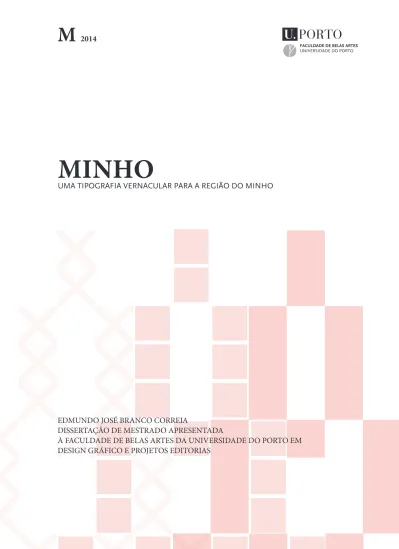
MINHO
UMA TIPOGRAFIA VERNACULAR PARA A REGIÃO DO MINHO
EDMUNDO JOSÉ BRANCO CORREIA
The main purpose of this dissertation is to show how the design of a typeface can reflect the identity of a region; in this case the region of Minho.The present work shall be guided by the question of whether a typeface can reflect the cultural identity of a place.
Minho region has strong traditions such as the gastronomy, the architectural heritage, religious festivities and folk dance. The folk dance is strongly related to “lenços dos namorados” ( Lovers’ han-dkerchiefs), where one can see some inscriptions related to the the-me of Love written in a poetic way.
The studied began with an analysis of the lettering used in the handkerchiefs and a vernacular base was used to draw the typeface. Thus, there was a relation between the typeface created by the lette-ring and the cultural identity of the place.
O propósito principal desta dissertação foi o desenho de uma tipogra-fia, que transparecesse a identidade da região do Minho. Teve como questão orientadora, como a tipografia pode refletir a identidade cul-tural de um local.
O Minho é uma região de fortes tradições: desde a gastronomia, passando pelo património arquitetónico, comemorações religiosas e, sobretudo o folclore. Foi através do folclore que chegamos aos lenços de namorados, e às suas inscrições em forma de verso, sempre relacio-nadas com o amor e a conquista.
Foi a partir das letras presentes nas frases bordadas nos lenços que se desenvolveu o estudo e se executou o projeto. Desta forma, partiu--se de uma base vernacular para o desenho da tipografia. Através do lettering presente nos lenços, foi também possível estabelecer uma li-gação entre a identidade cultural e a tipografia.